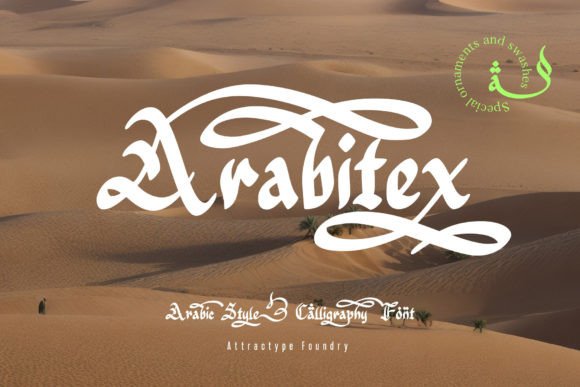
Arabitex
Jika anda sedang mencari aset berkualiti tinggi seperti Arabitex, pakej premium ini merupakan pilihan yang hebat untuk projek kreatif anda.
Dicipta dengan ketepatan, Arabitex menyediakan vektor yang bersih, tipografi yang licin dan lesen komersial untuk ketenangan fikiran.
Sama ada anda mencipta produk POD (Print on Demand), jemputan perkahwinan atau grafik media sosial, Arabitex amat bersesuaian.